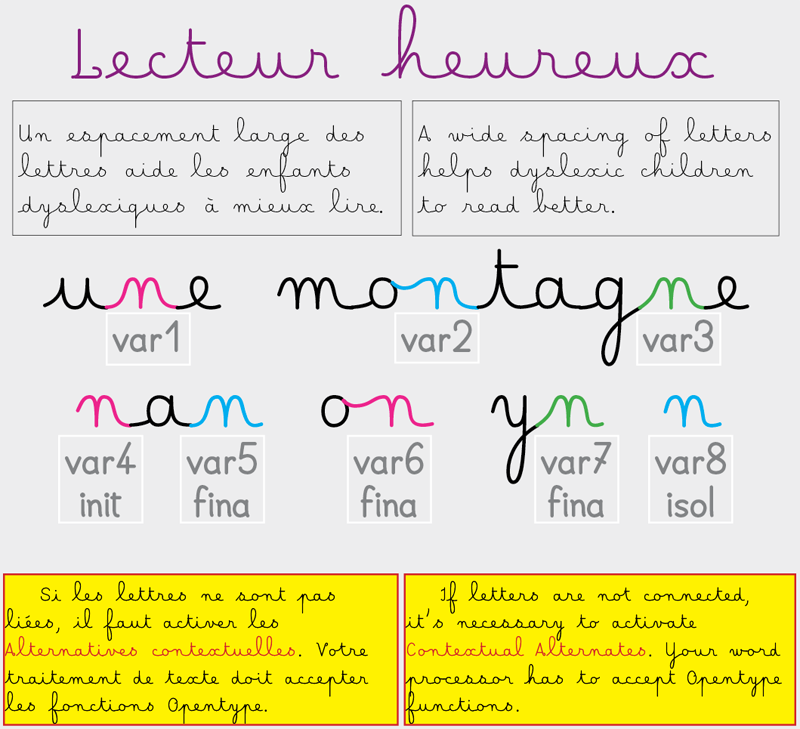
Categories | Script, School |
La lecture des enfants dyslexiques est facilitée si les lettres sont espacées. Lecteur Heureux est conçue pour eux. Cette fonte nécessite absolument que votre traitement de texte utilise les Alternatives contextuelles. Reading is easier for dislexic children if letters are spaced out. Lecteur Heureux is conceived for them. This font requires absolutely that your word processor uses Contextual Alternates. For a commercial or professional use, you have to take a license of Happy Reader : http://www.myfonts.com/fonts/jbfoundry/happy-reader%20/ More fonts here : http://www.myfonts.com/foundry/JBFoundry/ |